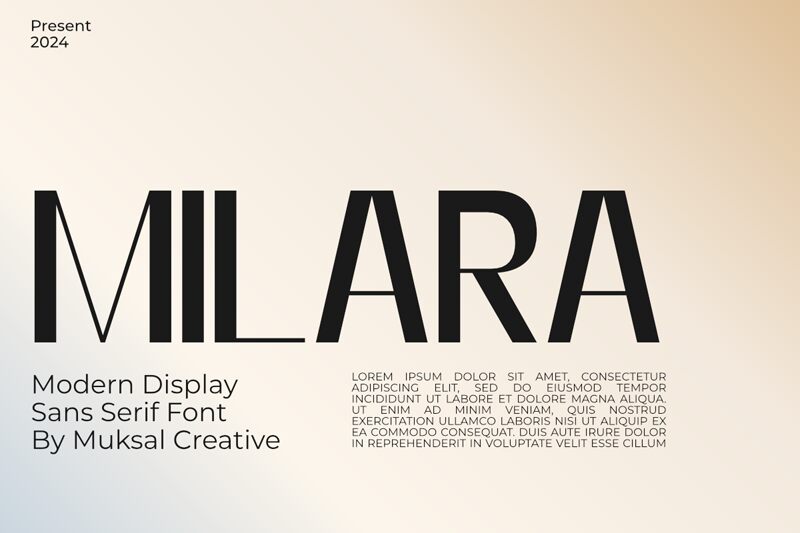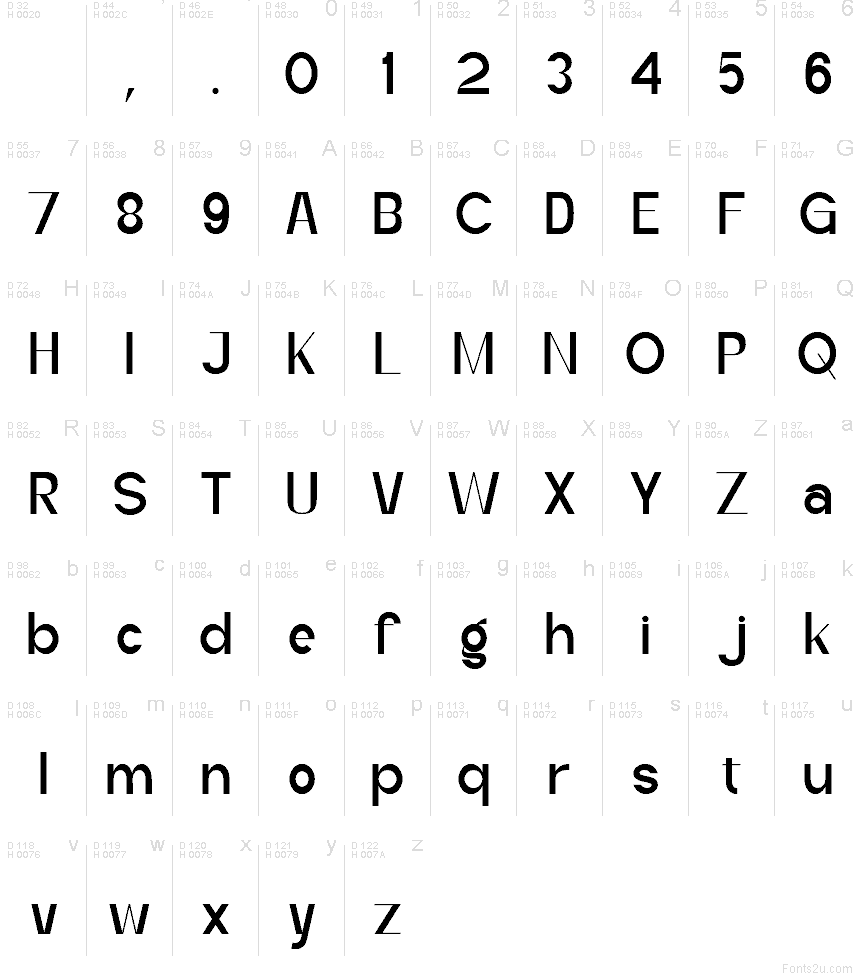
Milara Regular
Milara od Muksal Creative je bezplatné bezpätkové písmo definované ostrým kontrastom medzi výraznými rovnými ťahmi a veľkými zaoblenými tvarmi. Tento rytmus dodáva písmu elegantný, módny nádych, kde sa vzdušné vertikály stretávajú s jemnými kruhovými tvarmi, čím sa vyhýba rutinným štandardom bezpätkových písem.
Milara sa skvele hodí na kozmetické obaly, logá butikov, titulky časopisov, grafiku pre sociálne siete či elegantné etikety produktov. Kombinácia štíhlej konštrukcie a jemného oblého objemu dodáva krátkym slovám vycibrenú siluetu, vďaka čomu skvele ukotví branding alebo redakčné nadpisy bez potreby ďalšej dekorácie.